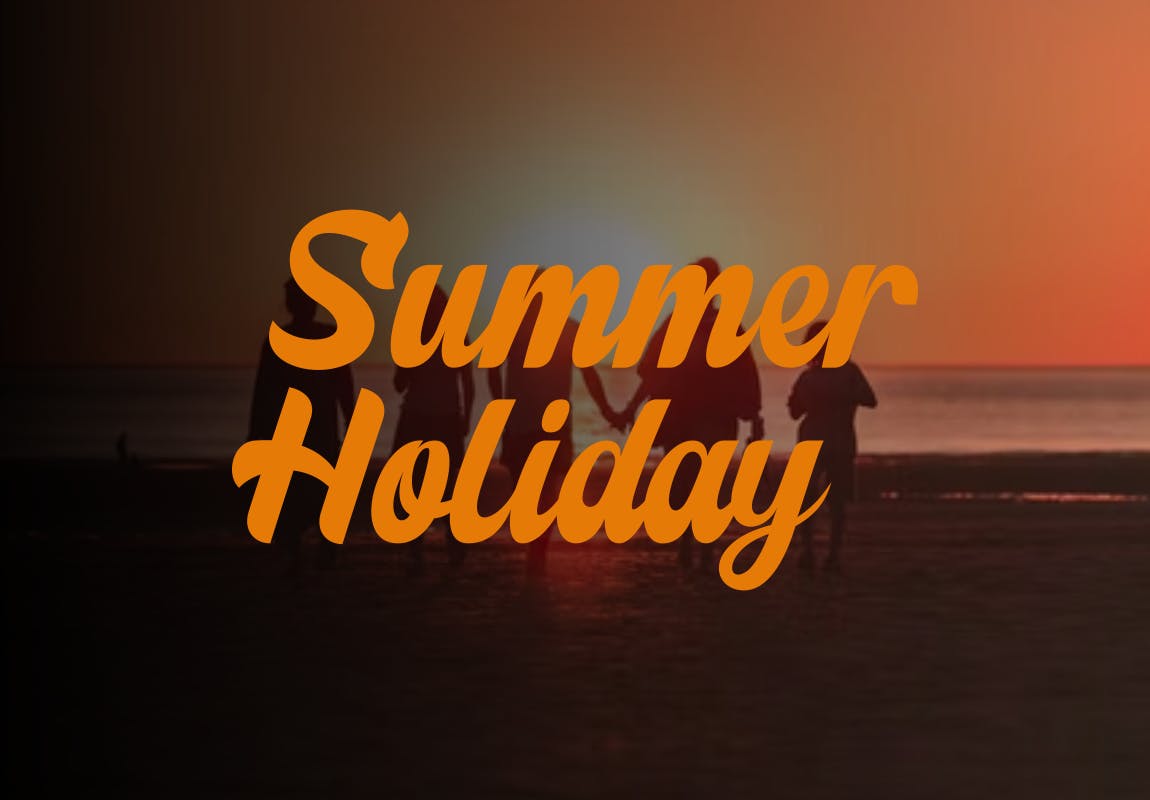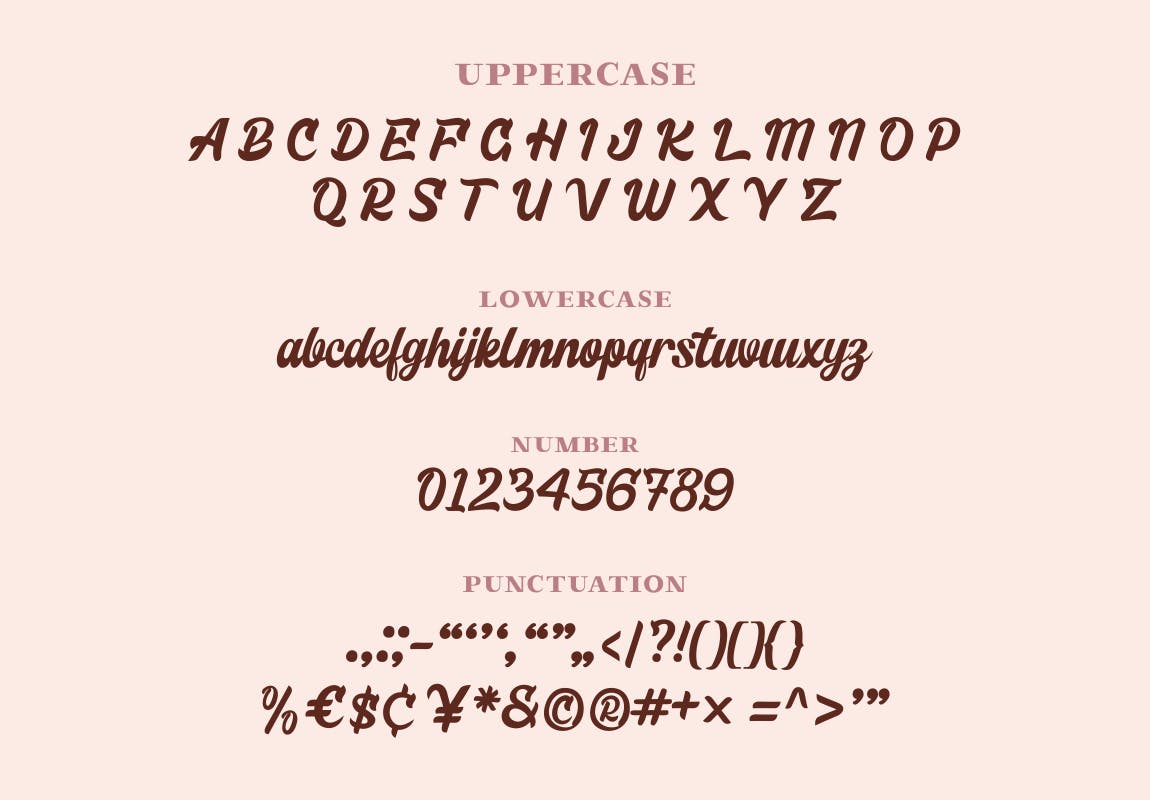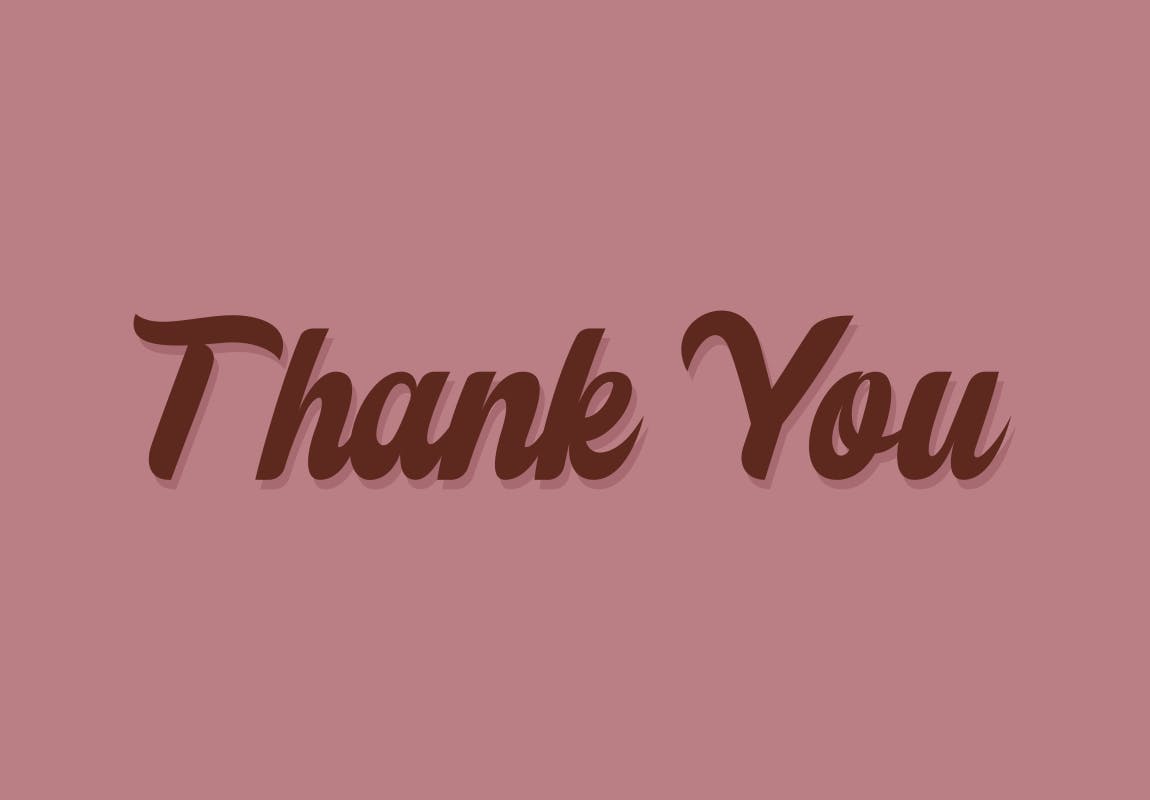
فونت هانیفا یک فونت مدرن برای نوشتار است که بهطور خاص برای استفاده در طراحی لوگو و سایر فرمهای رسمی مانند دعوتنامهها، برچسبها، مجلات، کتابها، کارتهای تبریک/عروسی، بستهبندی، مد، لوازمالتحریر، رمانها و هر نوع هدف تبلیغاتی دیگر طراحی شده است.